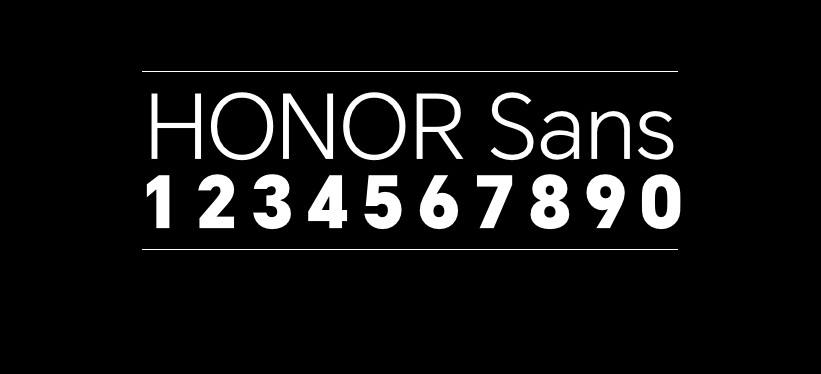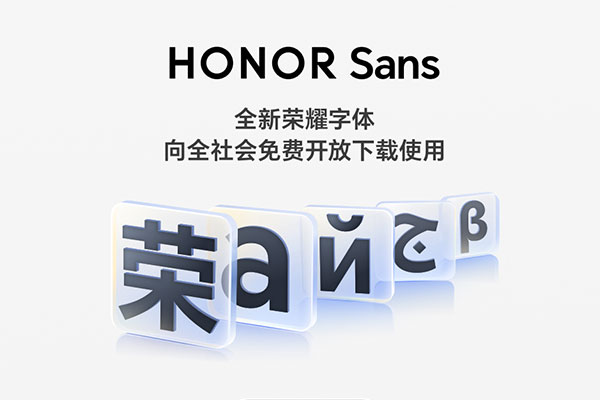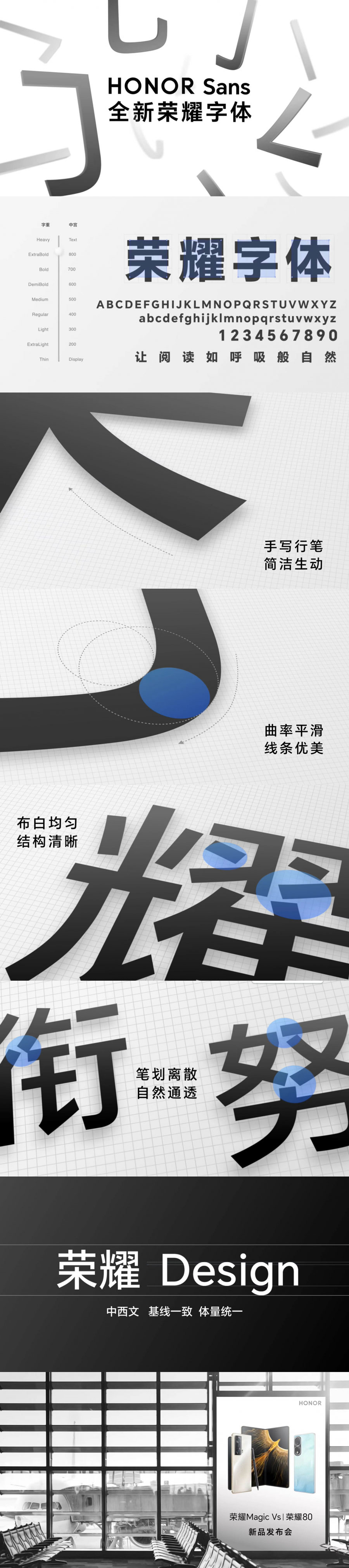
HONOR Sans
在11月的荣耀 MagicOS 7.0 发布会上,荣耀推出了一款全新的 HONOR Sans 字体,号称是业界首款支持字重和中宫双重无极可变的字体,将荣耀字体与 UI 融合,通过间距优化,让排版更整齐,层次更清晰。
荣耀将其称为”会呼吸的字体“。HONOR Sans 将面向全社会免费授权开放,覆盖全场景全人群使用,而且未来也将推送到荣耀全场景设备上。